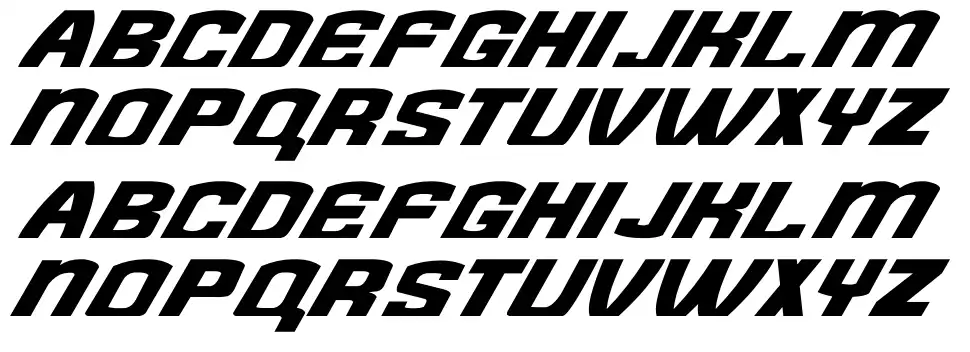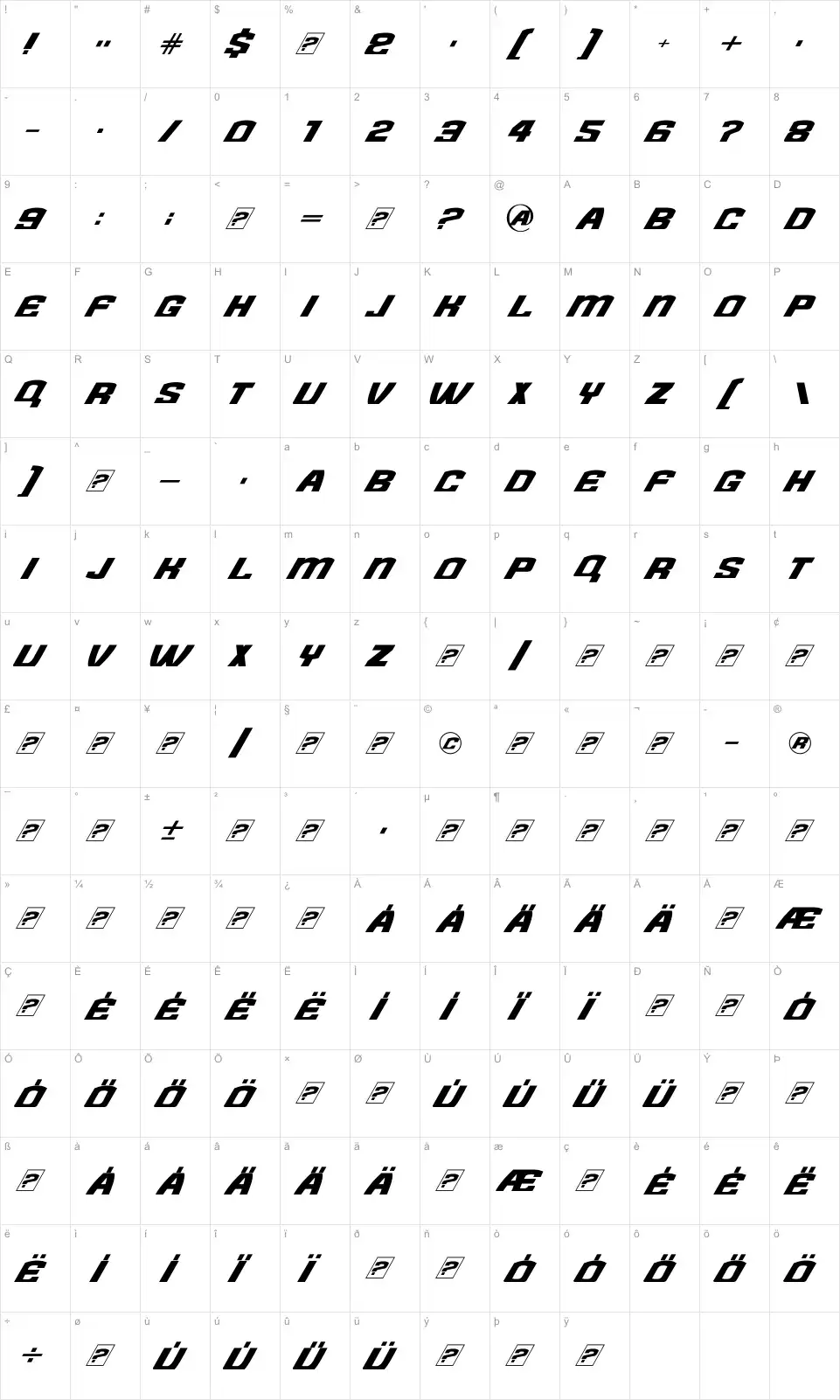
A fonte “Need for Font”, criada por Magique Fonts, é uma opção ideal para projetos tecnológicos e modernos. Se você está procurando por esta fonte, agora é possível baixá-la e experimentar seu visual online. Estamos falando de uma fonte do formato TTF, categorizada como Techno e diversas outras, e adotada recentemente em 13 de julho de 2022. Com um tamanho de apenas 7 KB, é uma opção leve e rápida para sua próxima criação digital. O site do designer, acessível através da página Facebook, é uma ótima fonte para encontrar mais opções de fontes criativas e modernas. Com apenas 1679 downloads, “Need for Font” está se destacando na comunidade de designers. Experimente agora e descubra por si mesmo por que esta font é uma escolha popular.